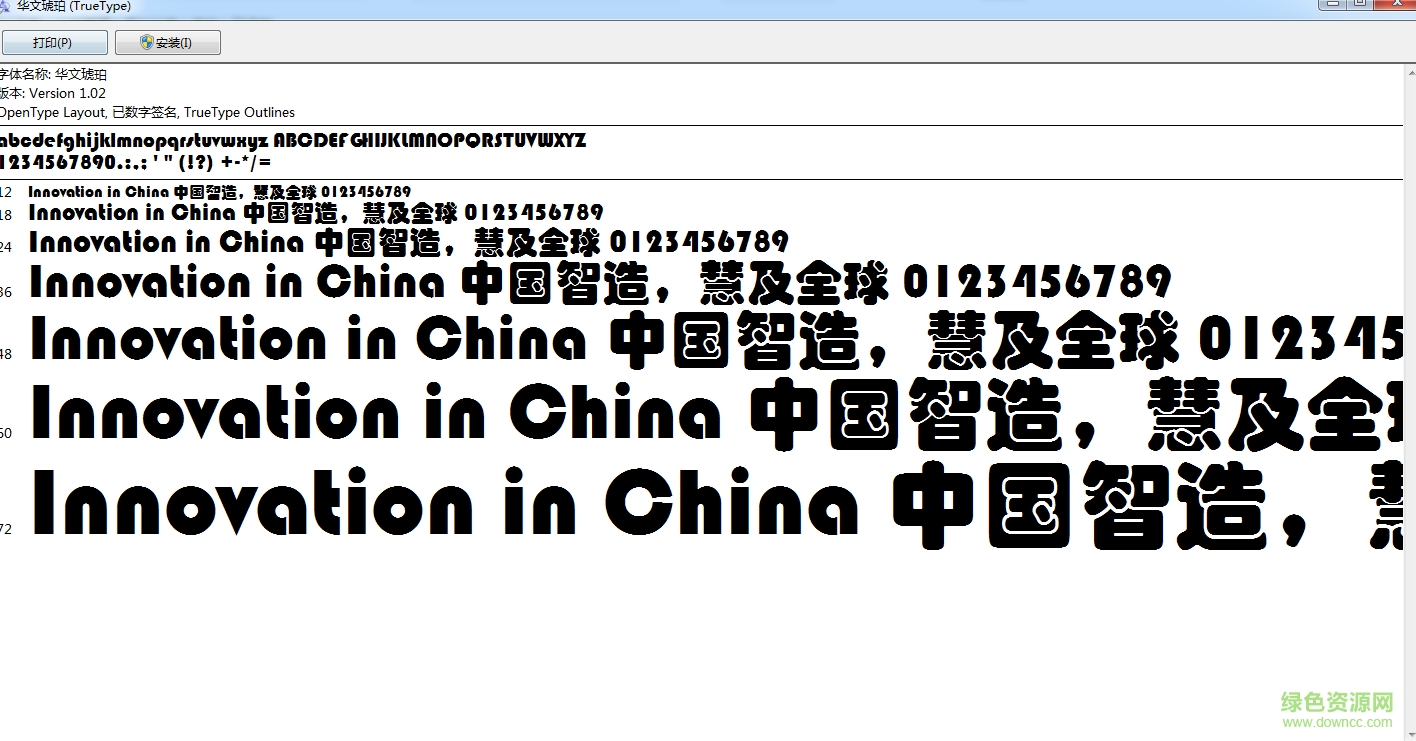
sthupo(華文琥珀)是一款與華文彩云比較相似的華文字體,點畫精致,結(jié)構(gòu)瀟灑,字形活潑而具有新意,辨識度高,能讓讓人看一眼就記住,需要的朋友快來綠色資源網(wǎng)下載吧!
sthupo字體特點
華文琥珀給人以多個筆畫拼湊、銜接在一起、富含層次感的感覺,美觀、清晰、醒目,給人的感覺既是柔滑細(xì)膩的又是粗壯有力的,確實稱得上“漂亮”字體。